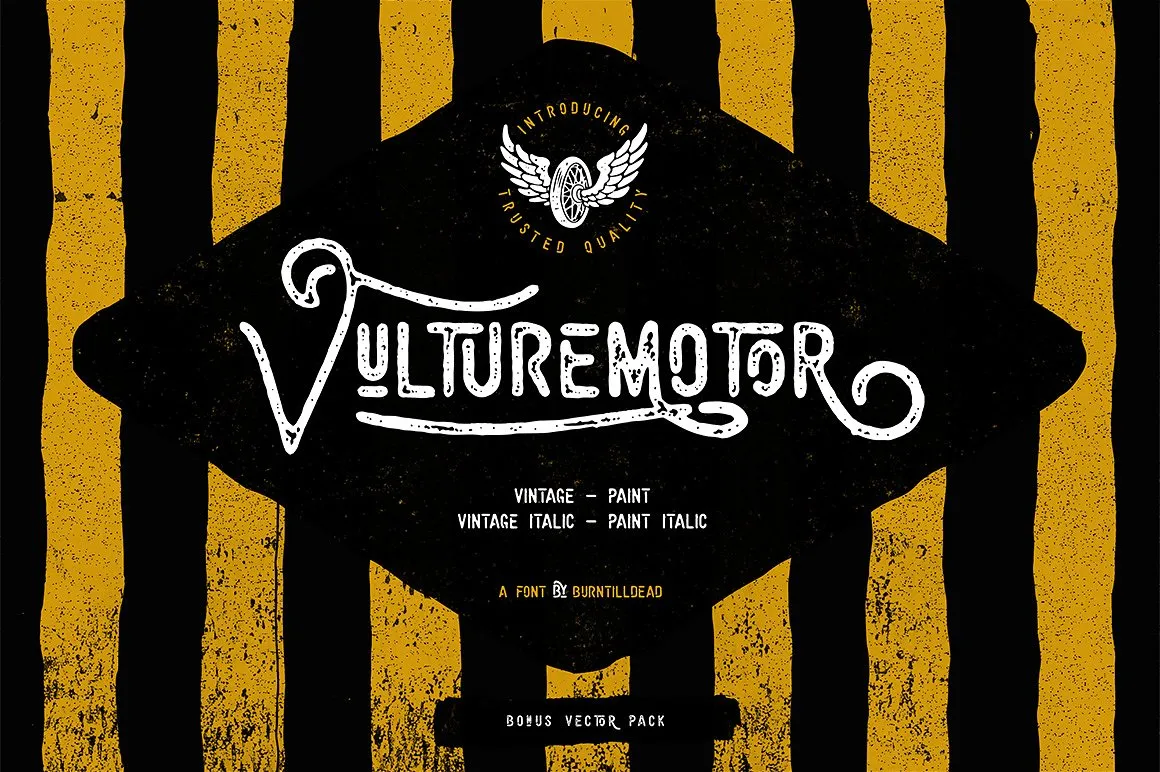
Vulturemotor Font – Download Grátis
Introduzimos a Vulturemotor Font! Desenhada e compartilhada pelo Hamilton, esta fonte Display é resultado de esforço meticuloso e consistência na sua manualidade. As letras são criadas à mão com uma caneta-pen, dando um aspecto naturalmente desorganizado, repleto de ligatura, ligatura disretizada, superscritos e subscritos, permitindo-lhe criar designs estilizados com facilidade. Além disso, os alternativos de caracteres oferecem uma excelente solução para displays criativos. É uma fonte perfeita para quem procura algo único e autêntico em seu design. Vulturemotor é a escolha ideal para qualquer projeto que busque um aspecto naturalmente desorganizado, combinado com estilos sofisticados e personalizados.